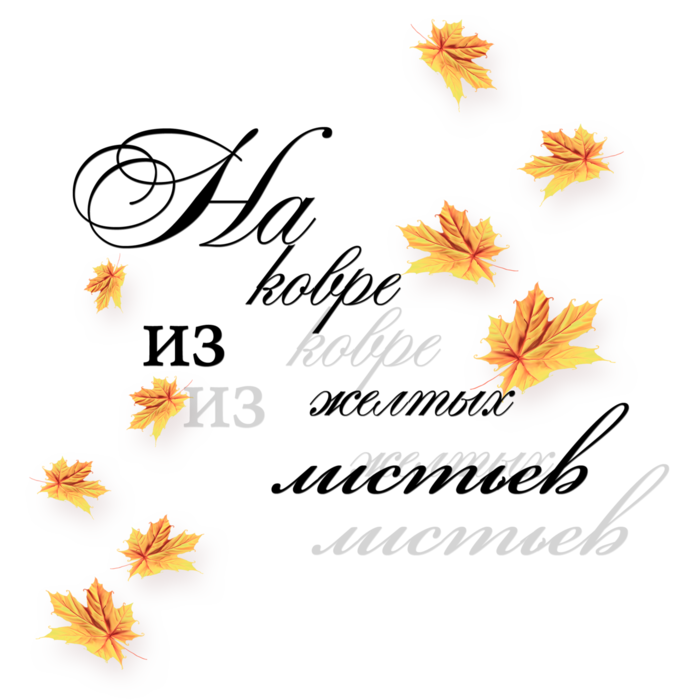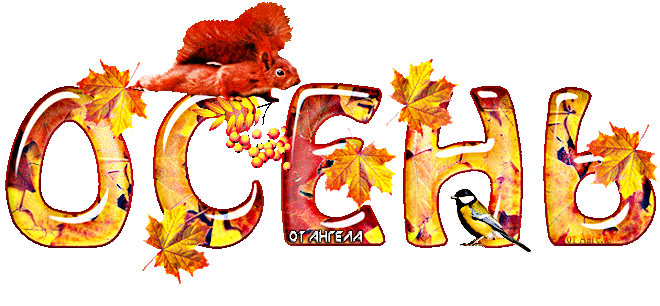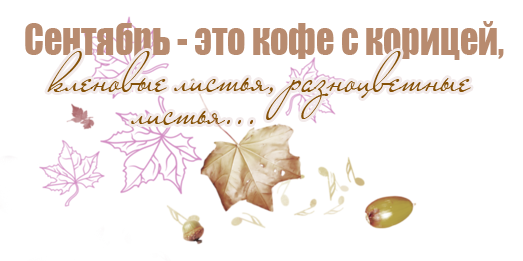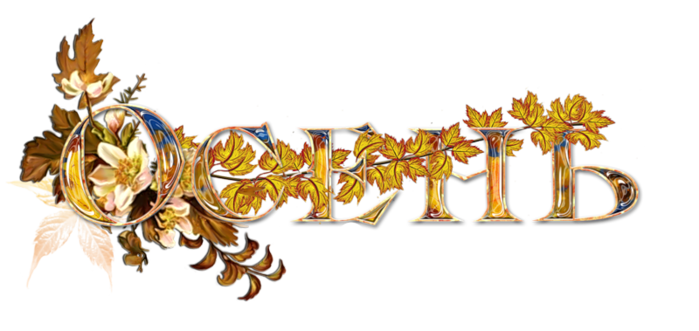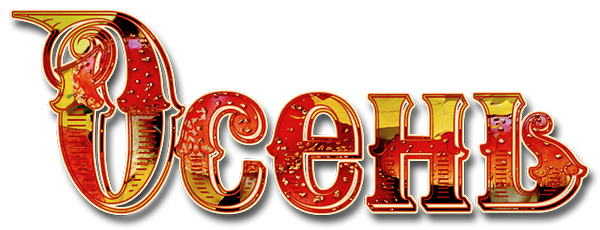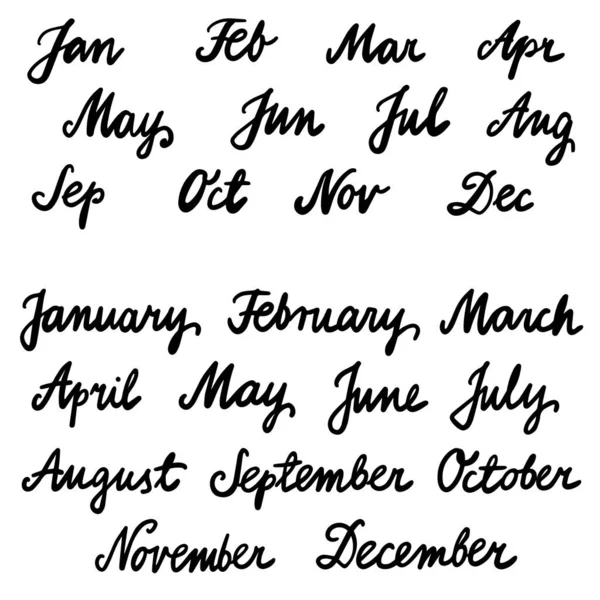
Сделайте слово красивым! / Хабр
Шрифты как языковая графика в CorelDraw.
Вначале было слово! Язык, разговорная речь плюс абстрактное мышление превратили человека умелого в человека разумного. Письменность связала отдельные группы людей в Общество. А в человеческом обществе принято не просто общаться, а делать это красиво. Отправлять душевные СМС-ки, вывешивать привлекательные ярлыки, передавать красиво оформленные документы. При этом использовать в своих посланиях и работах шрифт, соответствующий месту и времени.
За столетия развития искусства типографики созданы сотни тысяч шрифтов. Многие из них стали классикой и были переведены в цифровой формат — кто не знает гарнитуру Times, так любимую книжными издательствами (она помогает экономить бумагу). В газетах и журналах особенно часто используют семейства Pragmatica, Futura и Futuris Extra Bold. Все эти шрифты хороши, они легко читаемые. Но удобочитаемость и привычность далеко не всегда являются положительными свойствами.
А как насчёт попробовать самому с помощью одной из множества специализированных программ по созданию шрифтов? Разработка новых шрифтов — это целая наука со своими законами и правилами. Под силу ли новичку освоить их сразу — ведь придётся углубляться в дебри кернинга и трекинга, разобраться, что такое апроши и по каким правилам строятся собственно символы? К счастью, есть возможность только попробовать свои силы, а если появится серьёзный интерес — обратиться к «классике» шрифтового искусства. В таком случае для продолжающих мы рекомендуем не менее классическую книгу «Шрифты. Разработка и использование» (Барышников Г. М., Бизяев А. Ю., Ефимов В. В., Моисеев А. А., Почтарь Э. И., Ярмола Ю. А. М.: Издательство «ЭКОМ», 1997 г.).
Сделай сам
Дизайнер, использующий CorelDRAW, может позволить себе такую роскошь, как создание собственного, совершенно оригинального шрифта — набора печатных символов (глифов). В него входят строчные и прописные буквы, цифры, знаки препинания, математические и специальные символы. Есть разные форматы шрифтов, но возьмём для начала
Что нужно сделать, чтобы создать собственный оригинальный шрифт? Создать векторный набор: отрисовать, трассировать отсканированные изображения, преобразовать векторные элементы, применить векторные эффекты и последовательно экспортировать каждый символ в файл специального формата.
Технология создания шрифта в программе CorelDRAW трёхступенчатая:
1. Создание шаблона для разметки высоты, ширины, выступающих надстрочных и подстрочных элементов символов.
2. Отрисовка векторных символов — букв, знаков препинания, специальных символов.
3. Экспорт каждого символа в файл формата TTF с указанием расположения каждого символа.
Начинаем с глифов
Давайте создадим декоративный шрифт с помощью модификации существующих символов, применим некоторые интерактивные векторные эффекты и создадим шрифт, отсканировав готовые символы. Сначала нам нужен комплект глифов. И начнём мы с создания многостраничного документа. Выбираем единицы измерения — пункты, размер документа — 750×750 пунктов. В диспетчере объектов создаём мастер-слой для шаблона. Всё, что размещено на мастер-слое, будет видимым на всех страницах документа. Устанавливаем направляющие, отступая на 30 пунктов от левого и нижнего края документа.
Рис. 1. Создание мастер-слоя для шаблона
Рис. 2. Шаблон буквы с выступающими надстрочными и подстрочными элементами после применения эффекта «искажение»
Содержимое мастер-слоя будет видимо на всех страницах документа.
Каждый символ — в данном случае букву — будем размещать на отдельной странице, «вытаскивая» его из таблицы символов и применяя заготовку эффекта «искажение». После применения искажения каждый символ необходимо перевести в кривые.
Рис. 3. Вставляем из таблицы символов букву «А», применяем эффект «искажение», а символ переводим в кривые
Эти операции повторяем, пока не будут созданы все прописные буквы. В результате появляется многостраничный документ. Для строчных букв можно создать ещё один шаблон и работать в отдельном многостраничном документе.
При создании символов с «наклонными» элементами, например, русской буквы «Д», лучше сдвинуть символ до края листа за вертикальную направляющую. Так удастся уменьшить расстояние между парой символов — буквой Д и предшествующей ей буквой. Иначе из-за наклона расстояние в паре «ГД» зрительно будет казаться больше, чем расстояние между остальными буквами. Профессиональные разработчики шрифтов решают эту задачу точной настройкой расстояний между определёнными символами, задавая кернинговые пары.
При экспорте символов в файл задаём любые имена файла и гарнитуры шрифта, но, конечно, лучше, если имена совпадают. Можно создавать шрифты различных начертаний — жирные, наклонные. Можно собрать все часто используемые в определенных дизайнерских макетах символы в единый символьный шрифт, а можно создавать «другой» шрифт, генерируя отдельные буквы. Захочется — сделаем шрифт, имитирующий рукописные, иногда нарочито небрежные буквы. А можем собственный ужасный почерк отсканировать и затем доработать в векторном формате. В шаблоне, если хотим, поменяем расстояние между базовыми линиями, уменьшая или увеличивая тем самым расстояние между буквами и ширину самих букв.
От глифов к шрифту
Но вернемся к разработке нашего шрифта. Превращаем совокупность символов в шрифт.
Рис. 4. Итоговый многостраничный документ с прописными буквами-символами «колючего» шрифта